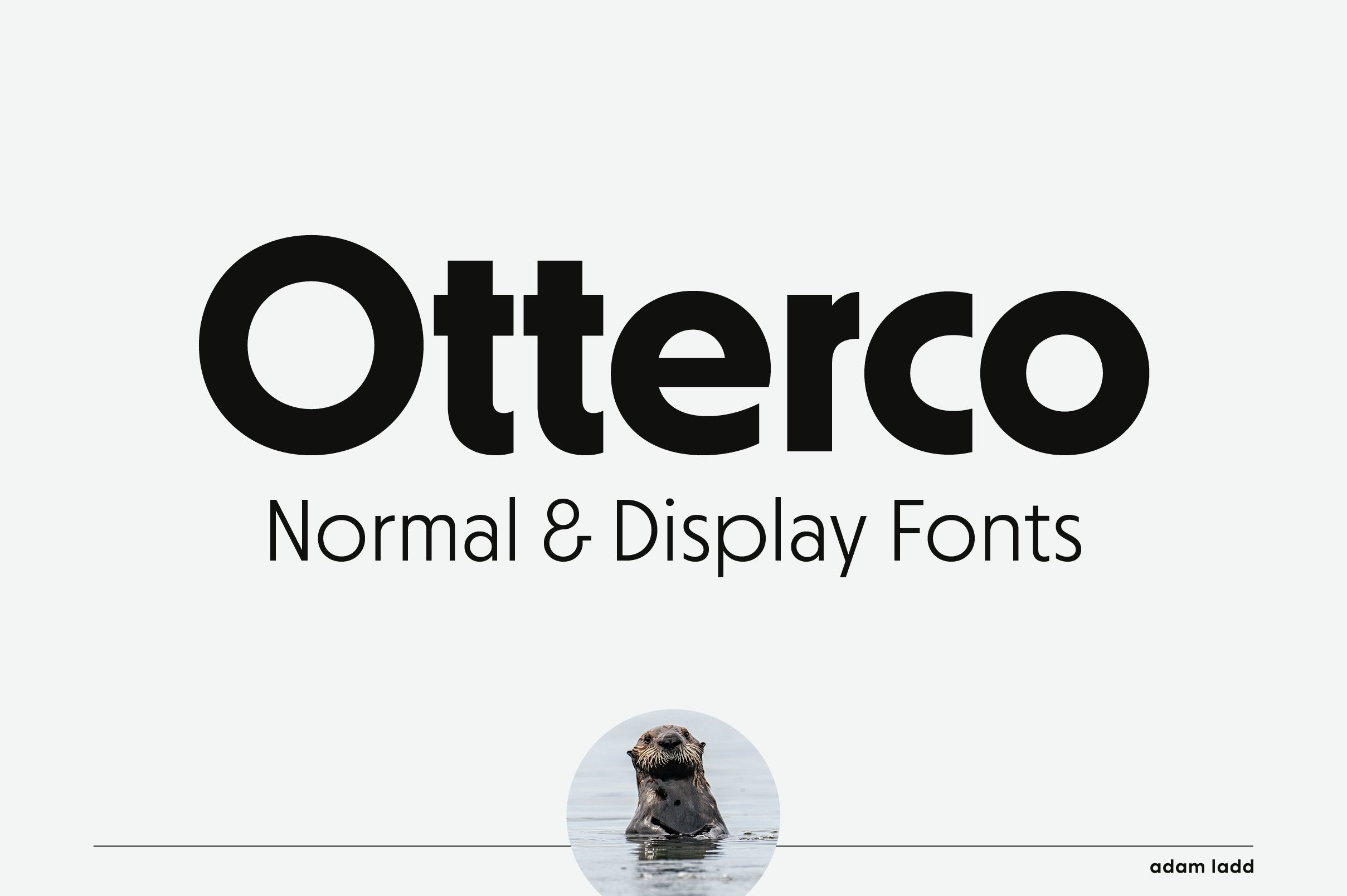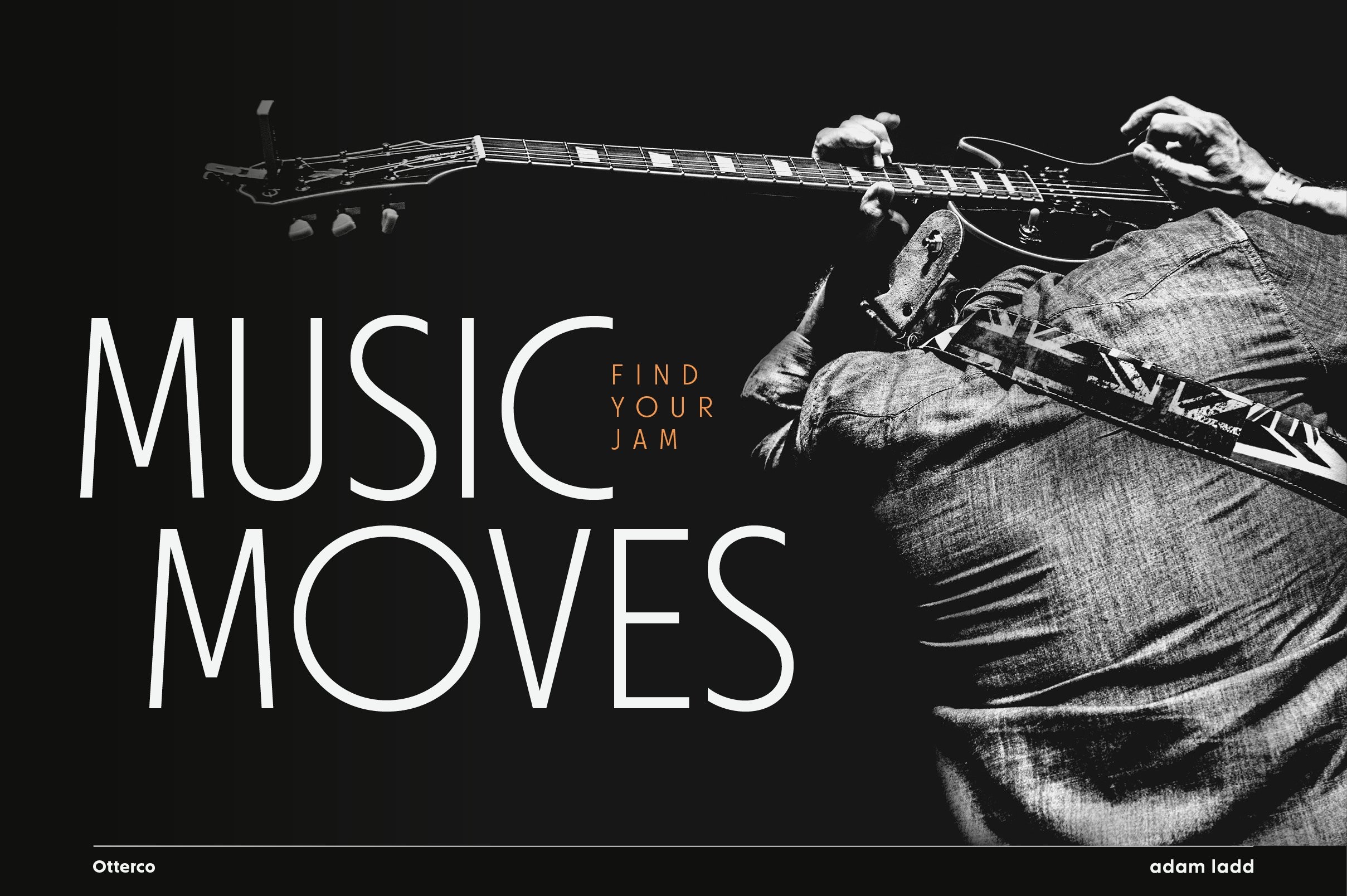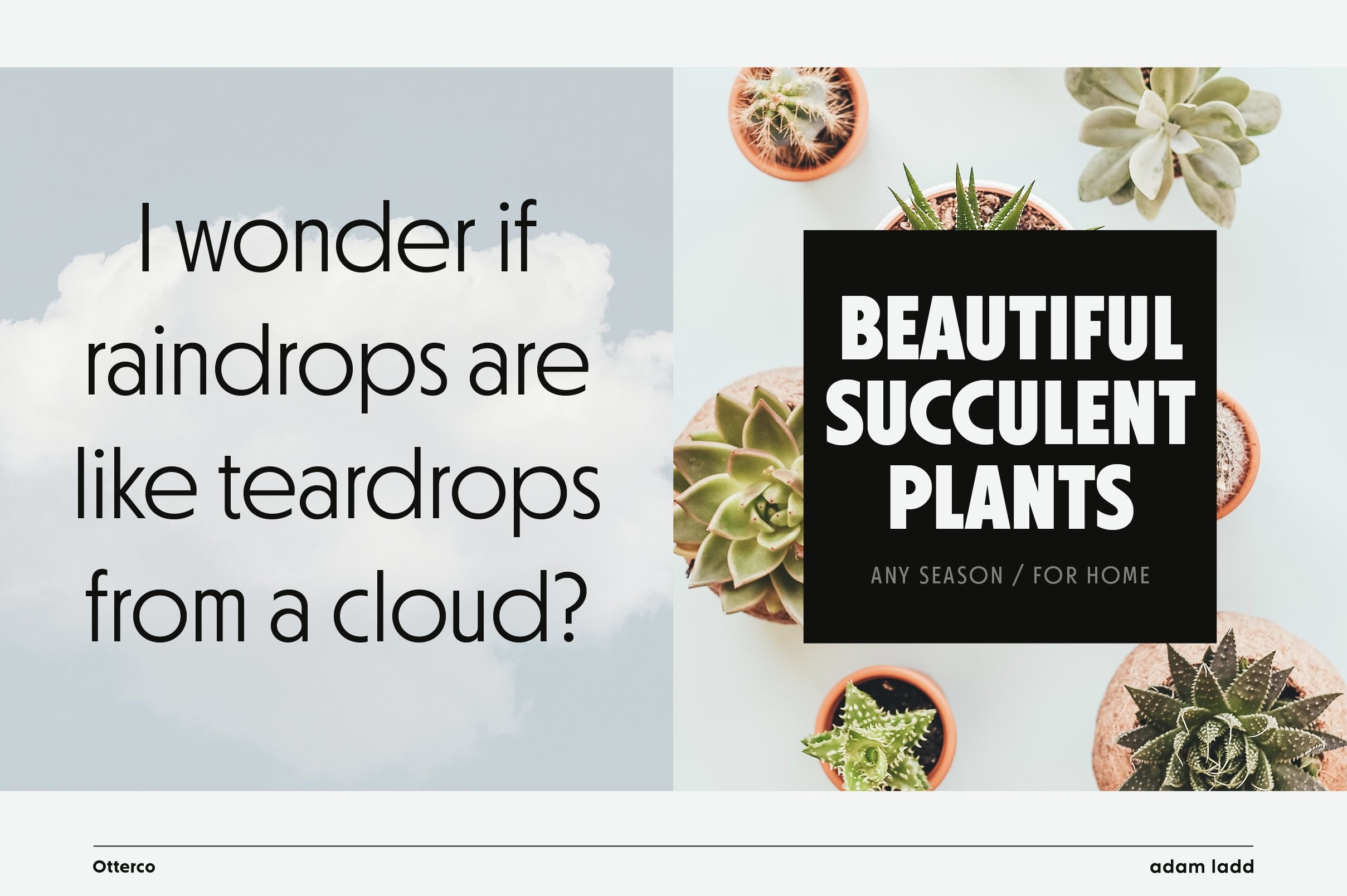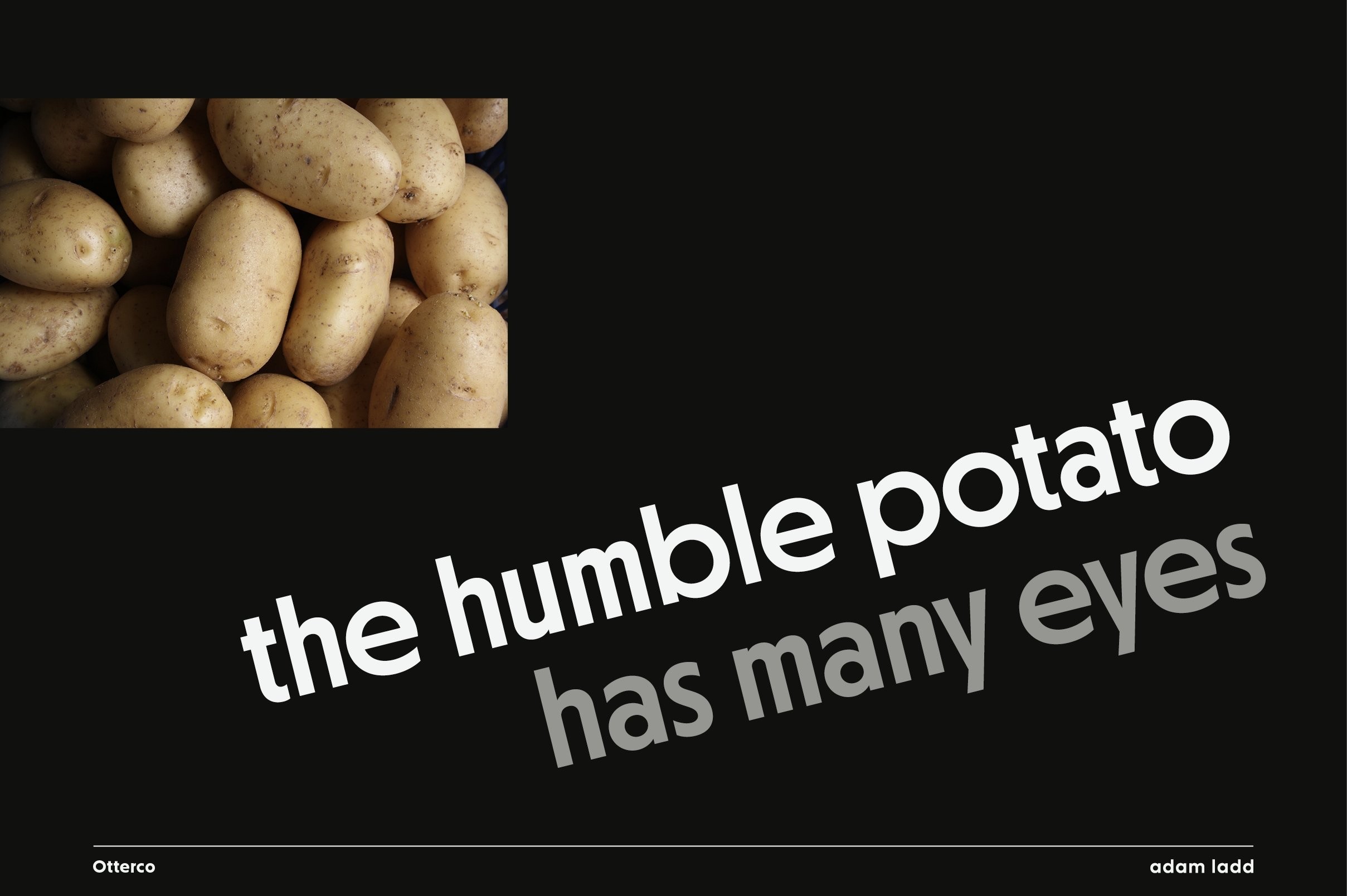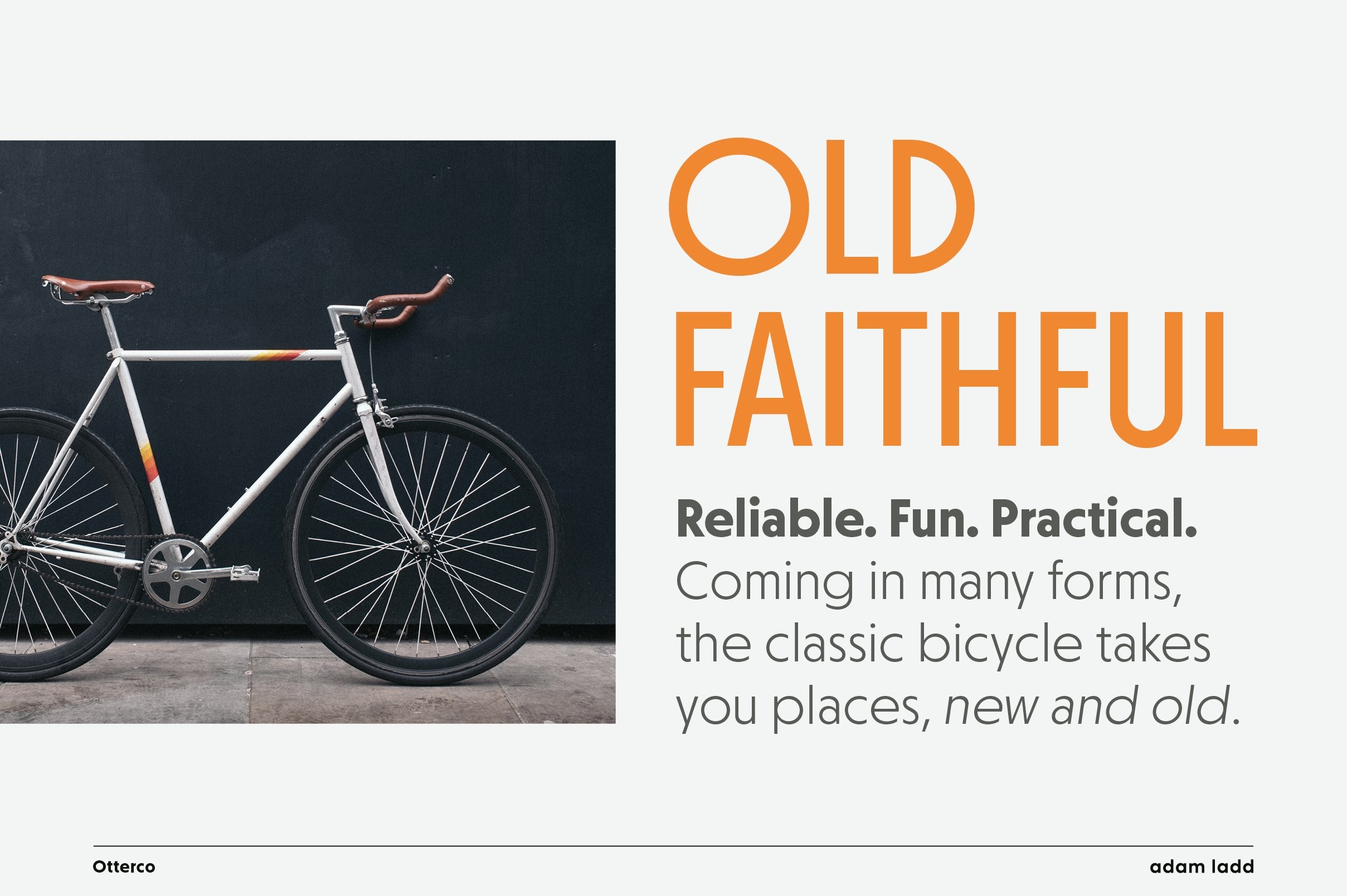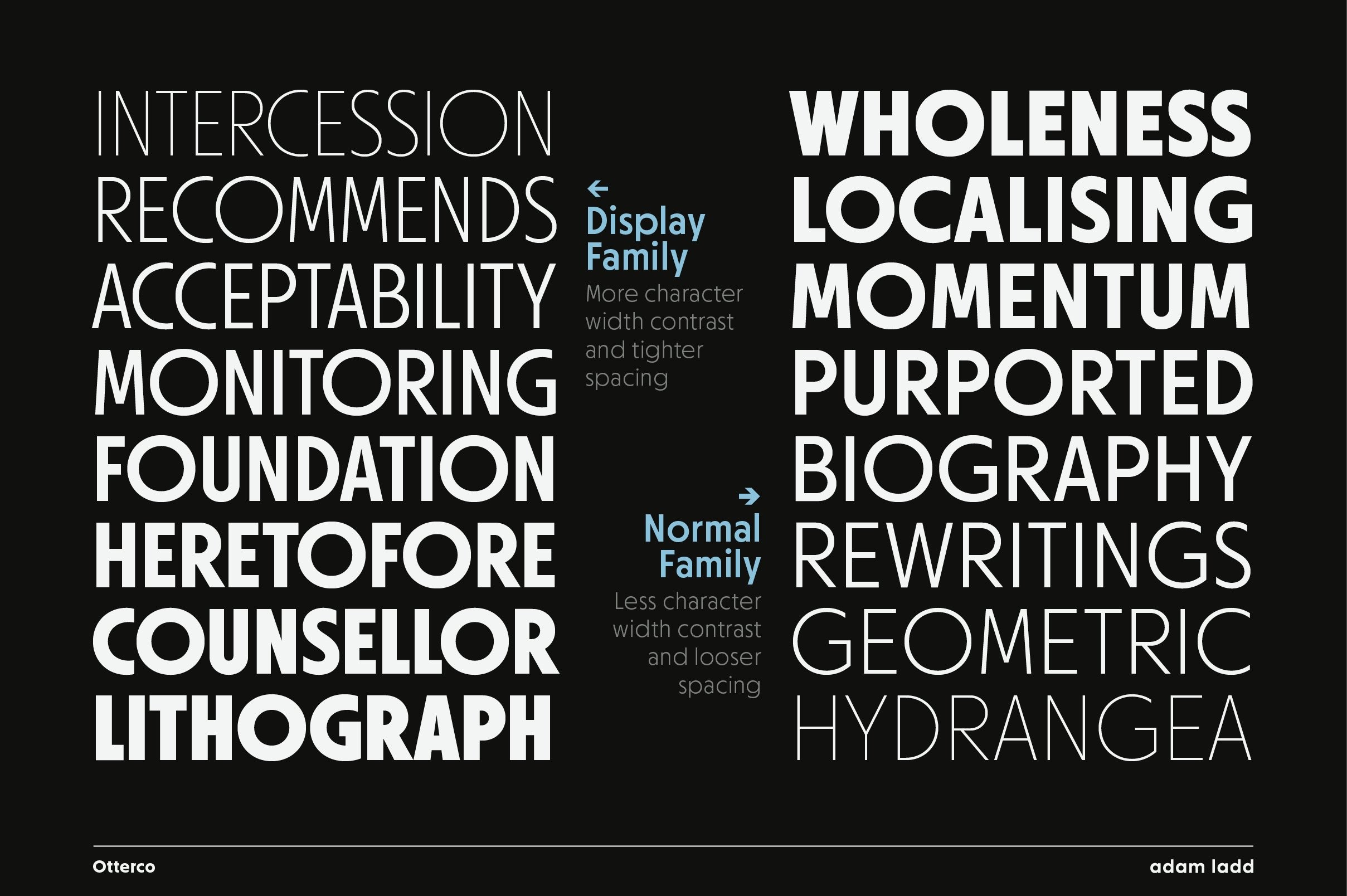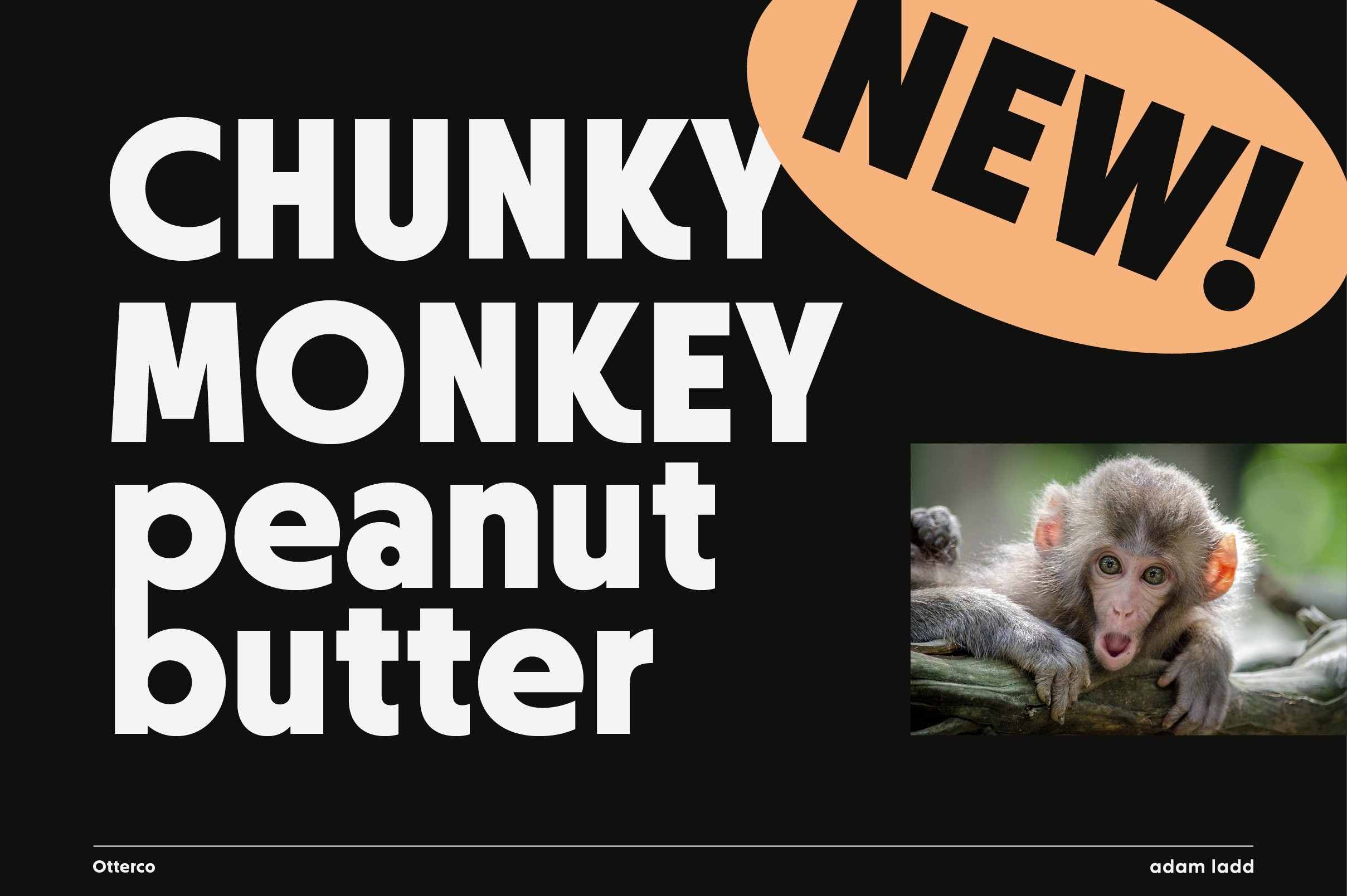
Otterco现代无衬线英文字体完整版
一款几何形无衬线字体,具有圆形和狭长字符,融合了复古和现代的特质。这种字体干净、中性但不乏味,结构具有较大的X-高度和较低的笔画对比度,可适用于各种应用。有普通和显示两个系列的字体,分别适用于不同的文本设置和语气。共有32种字体,包括细码到超粗码及斜体,适用于品牌、广告、包装、标题、杂志、网站、标志等多种应用场景。